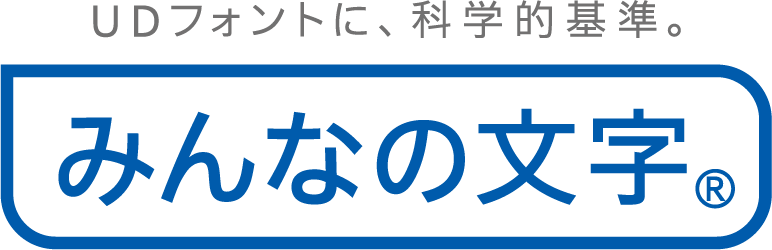
UCDA認証フォント「みんなの文字ゴシックPr6N」
イワタは、新製品となるUCDA認証フォント「みんなの文字ゴシックPr6N」を2020年11月17日に発売したことを発表した。
みんなの文字Pr6N 特徴
みんなの文字は、帳票や約款などの文字サイズが小さい印刷物でも、読みやすくすることを目的に開発したフォント。開発において、ISO13407人間中心設計のプロセスや、東京電機大学理工学部矢口博之准教授が開発した「IPO評価法」を採用、小さく使っても読みやすく文字の劣化に強い書体として2012年に完成した。また、UCDAが第三者の立場から客観的に評価・認証する「UCDA認証」を取得している唯一のユニバーサルデザインフォント(UDフォント)となる。
今回発表した「みんなの文字Pr6N」は、Adobe-Japan1の最新規格に対応したOpenTypeフォントです。収録文字数は、現行の「みんなの文字」Std版9,362文字(みんなの文字外字8文字含む)から、23,068文字(元号令和合字横用・縦用+みんなの文字外字8文字含む)と大幅に増えた。その他、標準字形は最新JIS規格のJIS2004字形に準拠し、Windows、Macなどの最新OSでの文字表示や異体字表示(IVS)にも対応しており、より幅広い文字表現が可能となっている。
みんなの文字ゴシックPr6N
4書体(L / R・R2 / M)